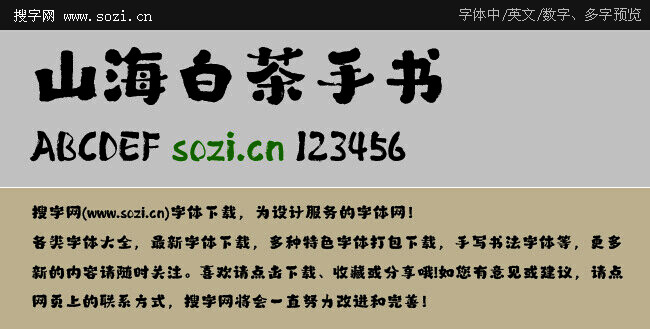
山海白茶手書
搜字網(wǎng)提供一款山海白茶手書中文書法字體下載,山海白茶手書是一款手寫風(fēng)格的書法字體,這款字體的在傳統(tǒng)毛筆字體上融入卡通書寫感,書寫手法輕盈流動,用筆輕松隨性,整體給人一種放松柔美的視覺效果。適合包裝設(shè)計、海報設(shè)計、廣告設(shè)計等應(yīng)用。